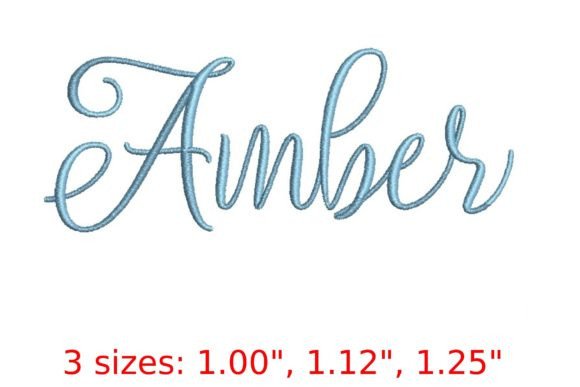
Amber Embroidery Font
การค้นหาองค์ประกอบการออกแบบที่เหมาะสมอาจเป็นเรื่องท้าทาย แต่ Amber Embroidery Font นำเสนอคอลเลกชันที่โดดเด่นซึ่งช่วยยกระดับงานของคุณได้ทันที
สร้างขึ้นอย่างแม่นยำ Amber Embroidery Font ให้เวกเตอร์ที่สะอาด พิมพ์ตัวอักษรที่ราบรื่น และใบอนุญาตเชิงพาณิชย์เพื่อความสบายใจ
ไม่ว่าคุณจะสร้างผลิตภัณฑ์ POD (Print on Demand) คำเชิญงานแต่งงาน หรือกราฟิกโซเชียลมีเดีย Amber Embroidery Font ก็เหมาะสมอย่างยิ่ง
เคล็ดลับจากผู้เชี่ยวชาญ: รวมองค์ประกอบเหล่านี้กับฟอนต์เสริมเพื่อสร้างการออกแบบที่โดดเด่นและเป็นเอกลักษณ์